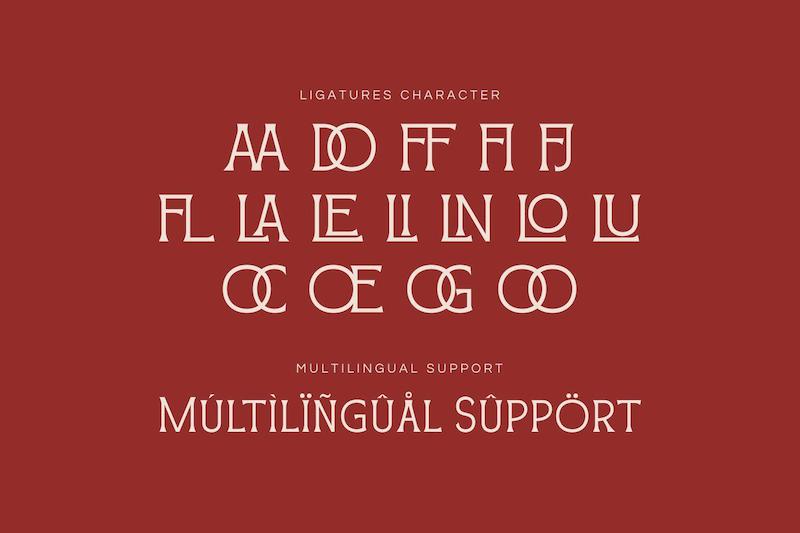
بلوسوم نوآر یک فونت دیسپلی زیبا با حروف لیگاتور است. این فونت برای طراحی لوگوهای خیرهکننده، نقلقولها، کارتهای دعوت، پستها، مطالب وبلاگ، پروژههای برندسازی، تصاویر مجله، تایپوگرافی و بسیاری موارد دیگر ایدهآل است.
کاراکترهای بزرگ و کوچک
کاراکترهای لیگچر چشمنواز
اعداد و نشانههای نگارشی
پشتیبانی از چند زبان
طبقهبندی: سریف
فاصلهگذاری: نرمال
اندازه بهینه: هر اندازهای